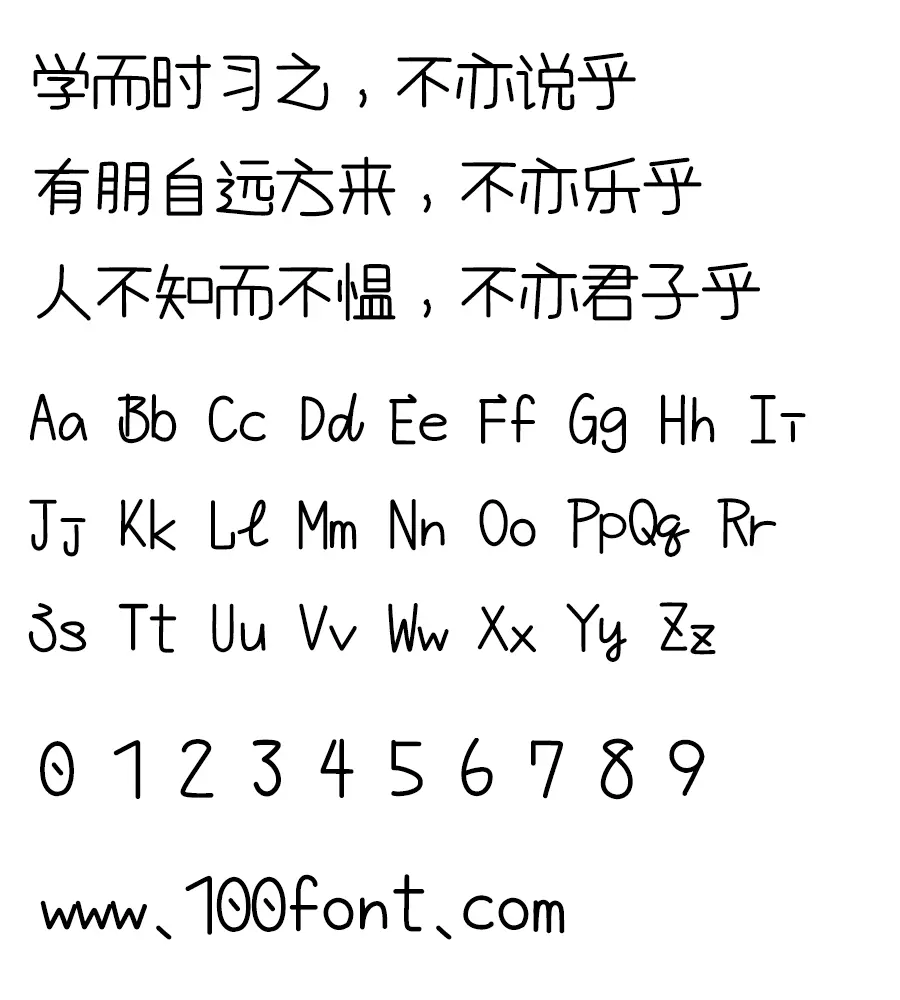
宅在家自動筆這款字體從2018年12月開始構想,於2019年7月完工,歷時半年。第一次嘗試製作字型,不是很好看。雖然中文字超級多,但是還挺有趣的。字體制作完成後,在記事本上試打,自己算是很滿意。平常在紙上寫字就是方方正正的風格,相試試看這種字體搬到電腦上用起來會是甚麼感覺。
我使用Medtbang Paint Pro繪圖軟件,手抖修正設定為35,手繪板是Viewontc的WoodPad,字型編輯軟件使用免費開源的FontForge製作。